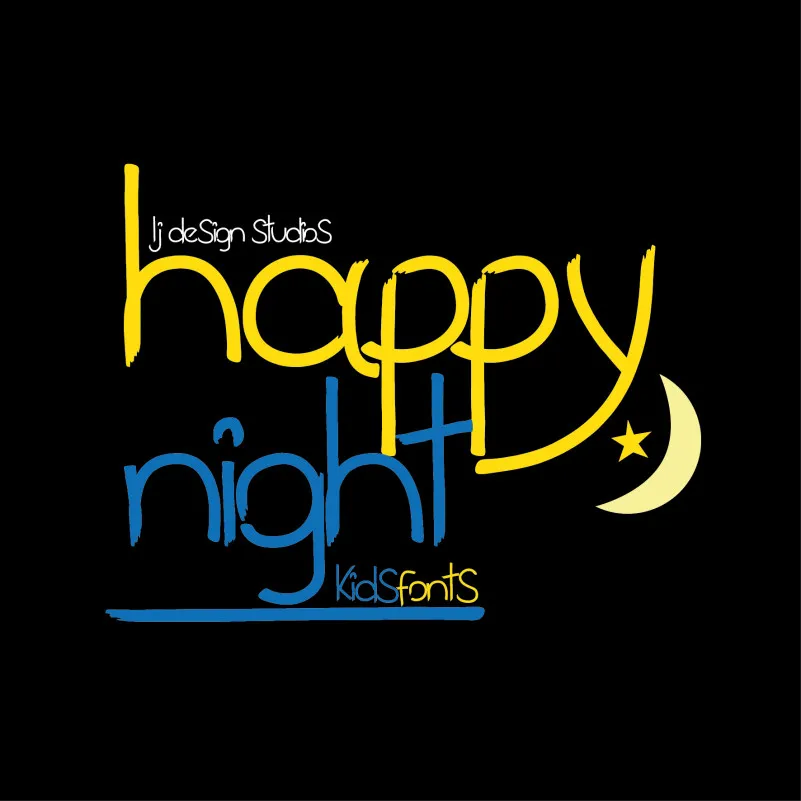
A fonte Happy Night é uma escrita cursiva perfeita para criar textos agradáveis e suaves à noite ou durante suas horas de relaxamento. Inspirada nos traços delicados dos cadernos pessoais, esta fonte tem um toque sereno que combina bem com mensagens amorosas, cartas pessoais, descrições de viagem tranquilas ou até mesmo aniversários e felicitações. Com Hamilton como seu designer, Happy Night oferece uma experiência de escrita única em sua categoria de fonts hand-writed, permitindo aos criadores um toque personalizado no design de seus projetos. Seja para textos individuais ou pequenos designs, esta font é perfeita para deixar um sabor especial na página. Não hesite em explorá-la como você busca adicionar uma sensação relaxante a qualquer projeto gráfico pessoal ou empresarial.